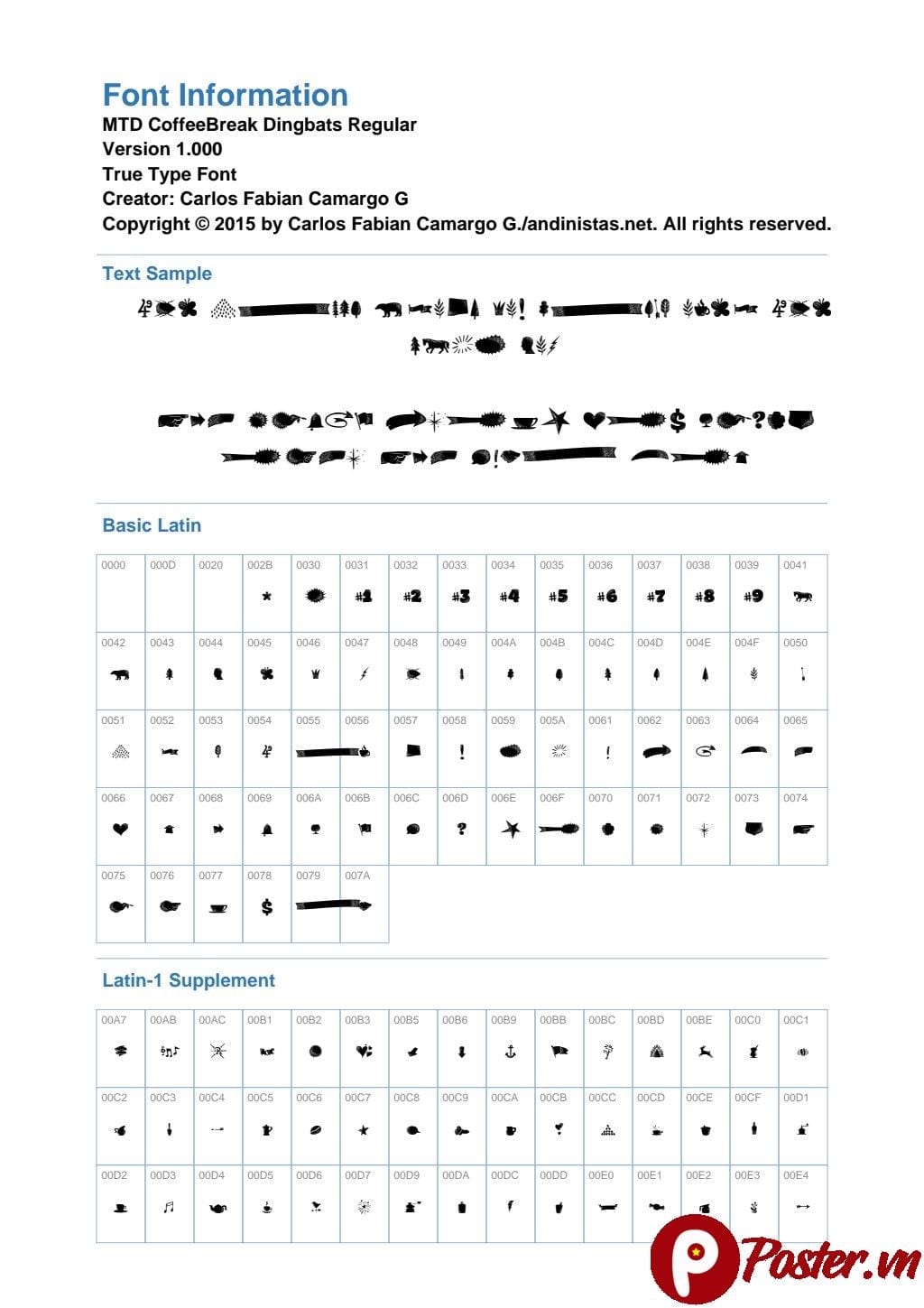
Giới thiệu về Font MTD CoffeeBreak Dingbats – Nét chấm phá độc đáo cho thiết kế của bạn
Trong thế giới thiết kế đồ họa rộng lớn, việc tìm kiếm một tài nguyên font chữ độc đáo có thể tạo nên sự khác biệt đáng kể cho tác phẩm của bạn. Hôm nay, Poster.vn hân hạnh giới thiệu đến bạn một viên ngọc quý: Font MTD CoffeeBreak Dingbats. Đây không chỉ là một bộ font chữ thông thường mà là một bộ sưu tập phong phú các ký tự dingbat được thiết kế thủ công, mang đậm phong cách vẽ tay (hand-drawn) và một chút hơi hướng grunge bụi bặm, phá cách. Đúng như tên gọi “CoffeeBreak”, bộ font này gợi lên cảm giác thư giãn, sáng tạo và đầy năng lượng của những giờ nghỉ giải lao bên ly cà phê, nơi những ý tưởng mới mẻ có thể nảy sinh.
Font MTD CoffeeBreak Dingbats do Carlos Fabian Camargo G sáng tạo, là một minh chứng cho sự sáng tạo không giới hạn trong nghệ thuật typography. Nó vượt ra ngoài những con chữ cái thông thường để mang đến cho người dùng hàng loạt các biểu tượng, hình vẽ mini vô cùng đa dạng: từ những tách cà phê, mũi tên cách điệu, hình ảnh động vật ngộ nghĩnh, cây cối, mặt trời, cho đến các biểu tượng cảm xúc và hình dạng trừu tượng. Mỗi ký tự đều được chăm chút với nét vẽ tự nhiên, tạo cảm giác gần gũi và cá nhân hóa. Nếu bạn đang tìm kiếm một công cụ để thêm điểm nhấn cá tính, sự vui tươi và một chút nét nghệ thuật vào các dự án thiết kế của mình, Font MTD CoffeeBreak Dingbats chính là lựa chọn không thể bỏ qua.
Bộ font này không chỉ dừng lại ở mặt thẩm mỹ mà còn mang lại giá trị ứng dụng cao cho nhiều lĩnh vực khác nhau, từ thiết kế thương hiệu cho các quán cà phê, tiệm bánh, cho đến các ấn phẩm truyền thông xã hội, poster quảng cáo, bao bì sản phẩm, thiệp mời, và thậm chí là sách thiếu nhi. Với MTD CoffeeBreak Dingbats, bạn có thể dễ dàng tạo ra những bố cục độc đáo, kể những câu chuyện bằng hình ảnh mà không cần tốn quá nhiều thời gian vẽ vời phức tạp. Hãy cùng Poster.vn khám phá sâu hơn về bộ font đặc biệt này và những gì nó có thể mang lại cho công việc sáng tạo của bạn.
Các tính năng nổi bật của Font MTD CoffeeBreak Dingbats
Font MTD CoffeeBreak Dingbats không chỉ là một bộ font đơn thuần mà còn là một kho tàng biểu tượng sáng tạo, sở hữu nhiều tính năng nổi bật cả về mặt kỹ thuật và thẩm mỹ, biến nó thành một công cụ không thể thiếu cho các nhà thiết kế:
1. Phong cách thiết kế độc đáo và cá tính
- Vẽ tay (Hand-drawn) và Grunge: Các ký tự trong font mang đậm dấu ấn thủ công, với nét vẽ tự nhiên, hơi thô ráp và hiệu ứng grunge nhẹ. Điều này tạo nên vẻ đẹp chân thực, gần gũi và một chút phá cách, rất phù hợp cho các thiết kế muốn thể hiện sự độc đáo và không theo khuôn mẫu.
- Chủ đề “CoffeeBreak” đầy cảm hứng: Đúng như tên gọi, font chứa nhiều biểu tượng liên quan đến cà phê, thư giãn như tách cà phê, hạt cà phê, hoặc các hình vẽ gợi cảm giác thoải mái. Đây là điểm cộng lớn cho các thương hiệu, quán cà phê muốn xây dựng hình ảnh gần gũi, ấm cúng và sáng tạo.
2. Kho tàng biểu tượng Dingbat phong phú
- Đa dạng các loại ký tự: Bộ font bao gồm một loạt các biểu tượng dingbat đa dạng, không chỉ giới hạn ở chủ đề cà phê. Bạn sẽ tìm thấy các loại mũi tên cách điệu, hình ảnh động vật (gấu, bò), cây cối, mặt trời, các biểu tượng cảm xúc (trái tim, ngôi sao), các ký hiệu tiền tệ, dấu chấm than, dấu hỏi và nhiều hình dạng trừu tượng khác.
- Ứng dụng linh hoạt: Sự đa dạng này cho phép bạn sử dụng font trong nhiều ngữ cảnh khác nhau, từ việc tạo điểm nhấn cho văn bản, thiết kế logo, biểu tượng, họa tiết trang trí, đến việc tạo ra các yếu tố đồ họa độc lập.